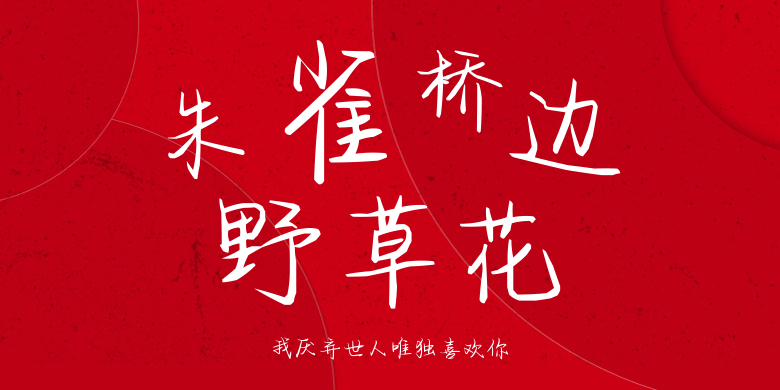
我厌弃世人唯独喜欢你
我厌弃世人唯独喜欢你,这款字体结构工整、笔画清晰,兼顾美观与易读性,适用于标题、正文、海报、包装、LOGO 等多种场景。字形优雅稳定,风格百搭耐看,适配日常排版与创意设计,让文字呈现更舒适、更具质感。我厌弃世人唯独喜欢你一笔一画,皆是细节,以均衡的比例、流畅的线条打造舒适视觉体验,字形端正大气,风格简约现代。无论是商业设计、品牌宣传还是日常排版,都能轻松驾驭,让文字更有格调与力量。我厌弃世人唯独喜欢你字体下载。